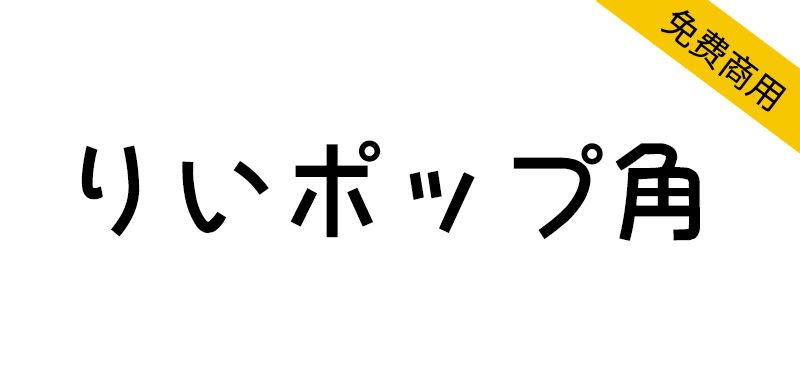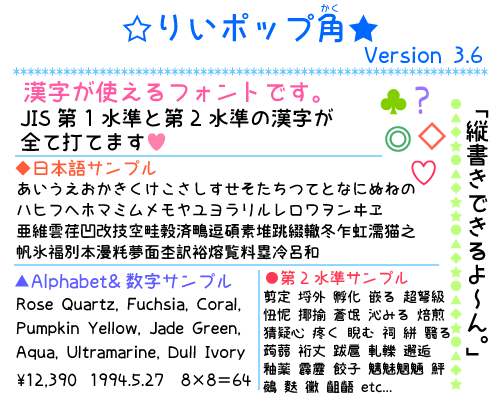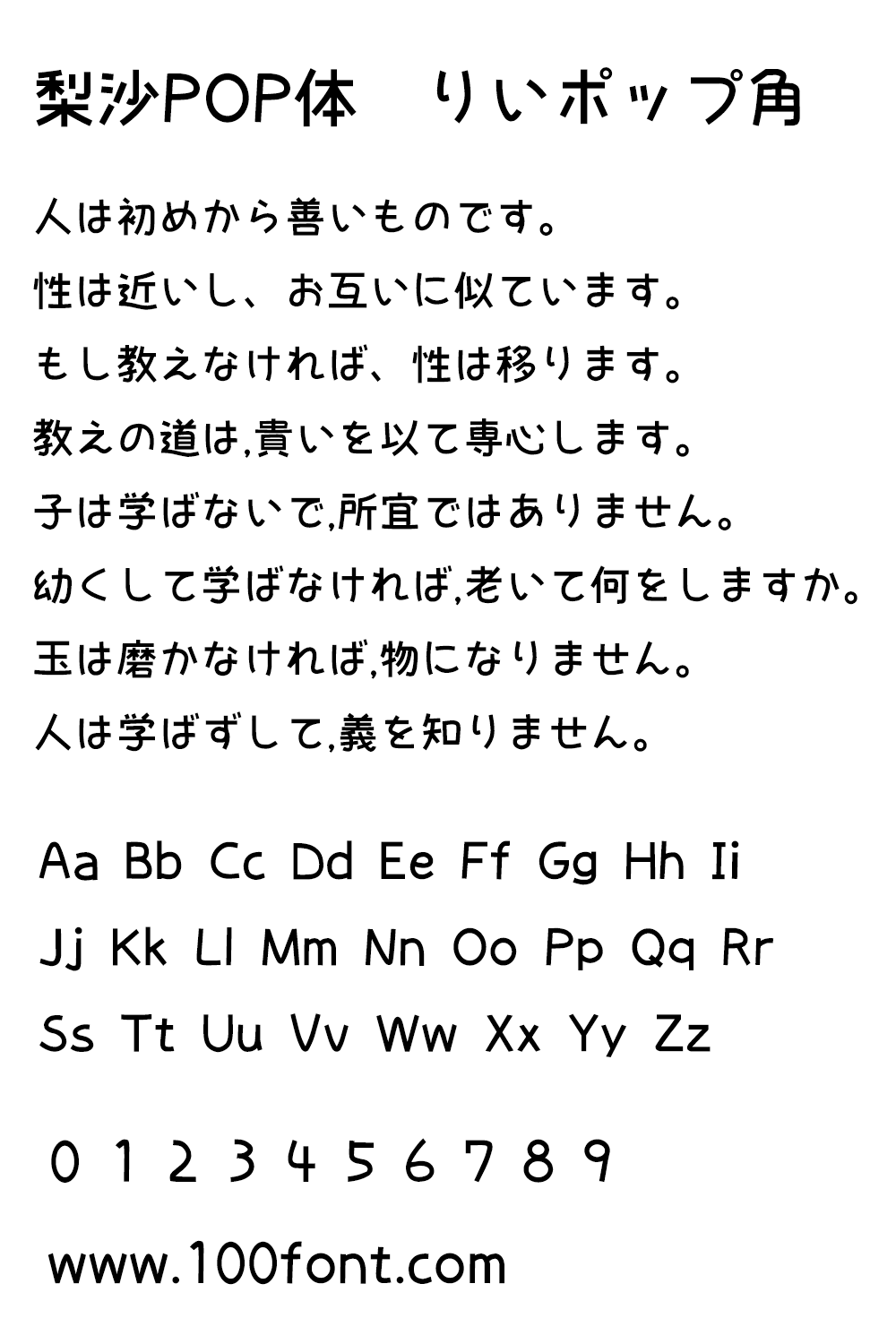
【梨沙POP体 りいポップ角】基于POP体概念的日文手写体
概念(?)是「女孩子的pop体」。虽然不知道是不是这样做的(笑)。
以容易亲近快乐气氛的字体为目标。字的形状是以纸上写的字(方案)为基础,用Adobe Illustrator制作的。
コンセプト(?)は「女の子っぽいポップ体」です。そのように作れたかはわかりませんが(笑)。親しみやすくて楽しい雰囲気のフォントを目指しました。
字の形は、紙に書いた字(案)をもとに、Adobe Illustratorで作りました。